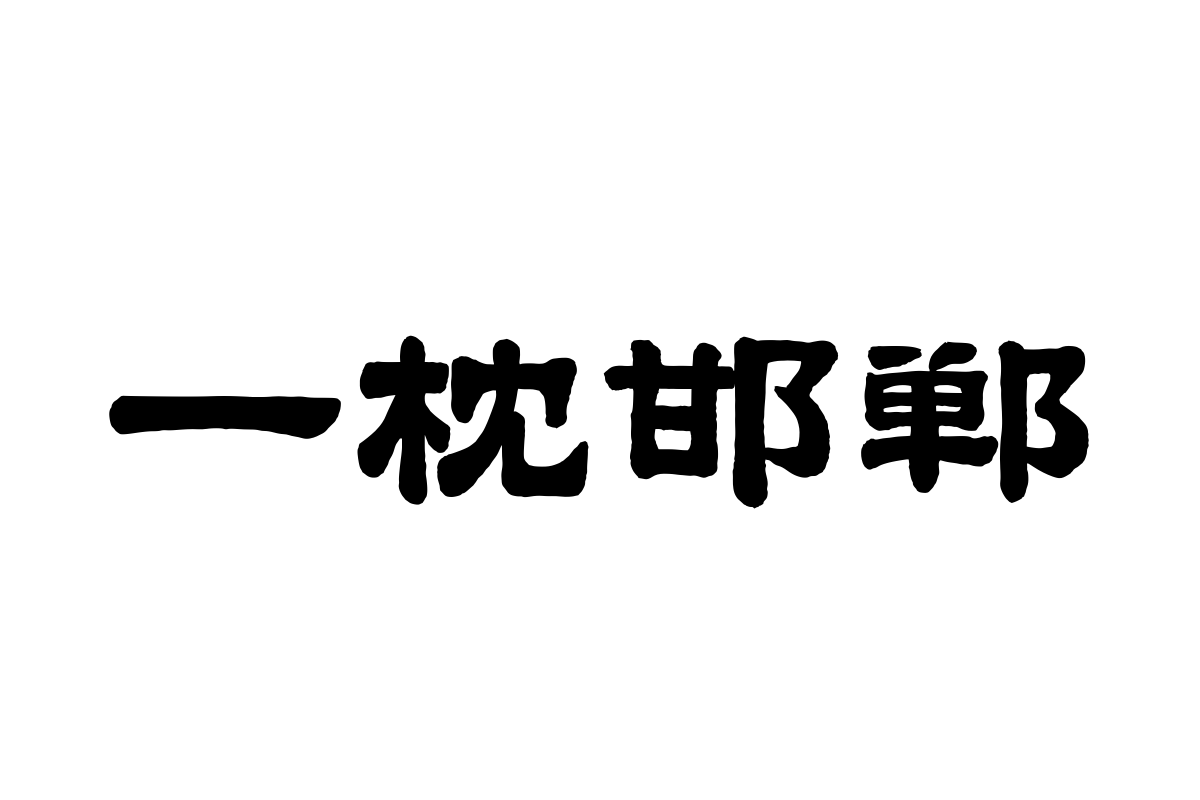
汉仪笔染润书字体是一款具有独特风格的中文字体,其特点如下:
1. 字形结构:汉仪笔染润书字体的字形结构紧凑,笔画粗细适中,给人一种简洁、明快的感觉。
2. 笔画特点:字体中的笔画流畅自然,没有过多的装饰性元素,使得整个字体看起来更加简洁大方。
3. 字间距:字体之间的间距适中,既不过于拥挤也不过于稀疏,使得文字整体看起来更加协调。
4. 风格特点:汉仪笔染润书字体的风格独特,既有传统书法的韵味,又不失现代感,适合用于各种需要书写的场景。
5. 适用场景:这款字体适用于标题、正文、广告等场合,能够为文字增添一份独特的魅力。